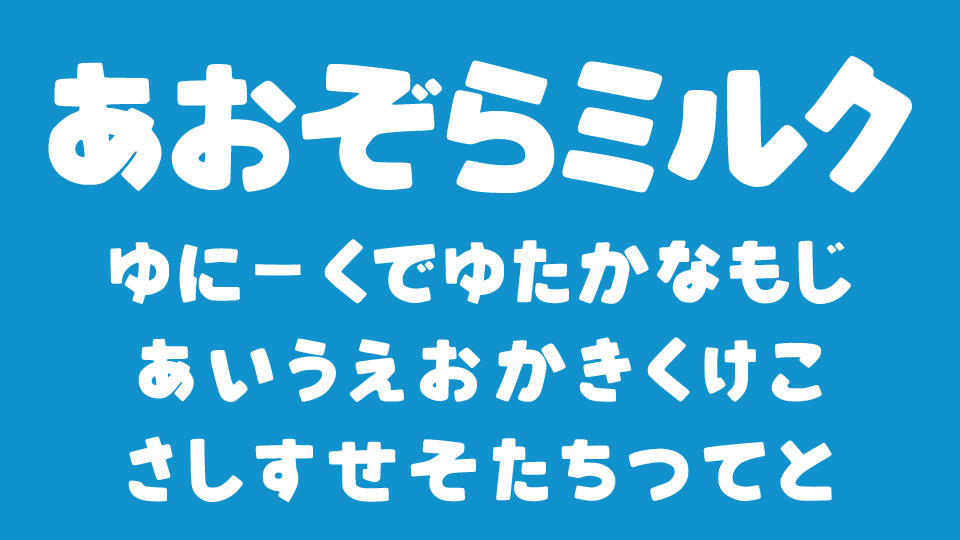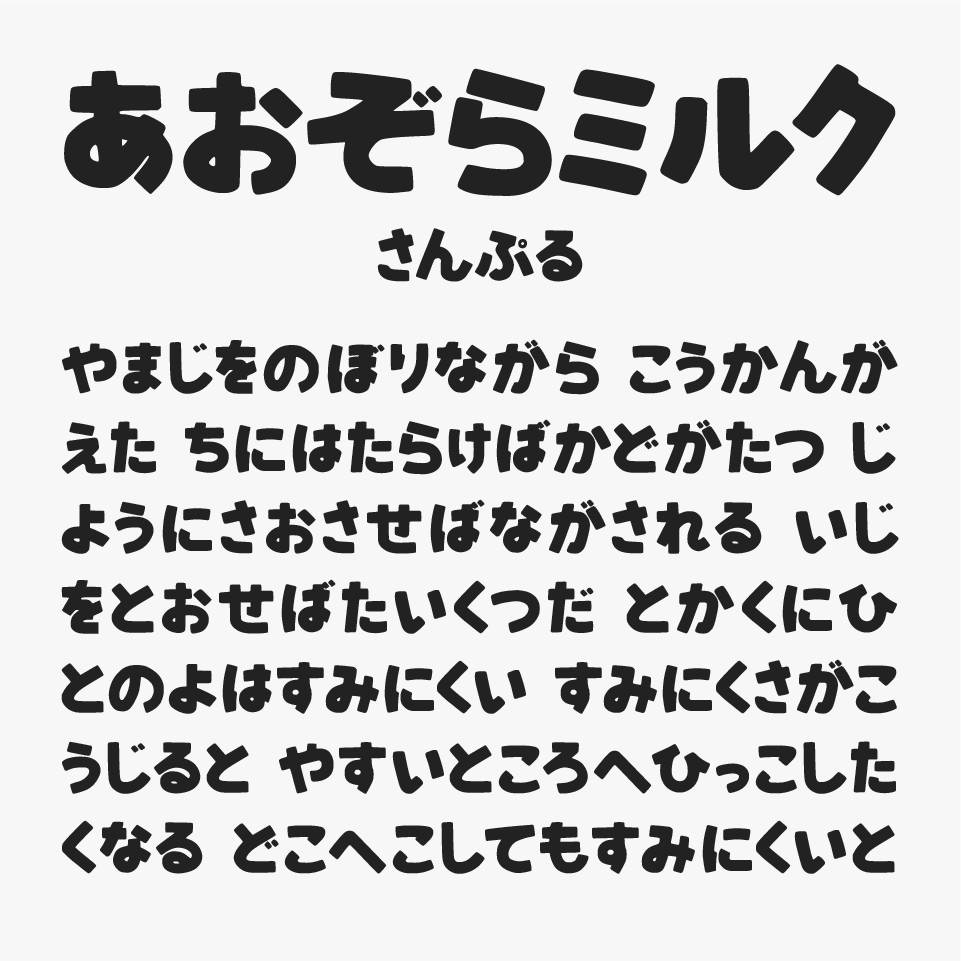
あおぞらミルク
あおぞらミルクフォントは、丸みを帯びた太いストロークが特徴的な、ポップで親しみやすいひらがなフォントです。
角をしっかり落とした字形は柔らかく膨らんでおり、手作りのようなクラフト感のある可愛らしいフォントです。
文字全体にゆったりとした余白があり、窮屈さをまったく感じなく、柔らかい雰囲気がとってもステキなデザインです。
収録文字は、ひらがな・カタカナ(ミ・ル・クの3文字のみ)が収録されています。